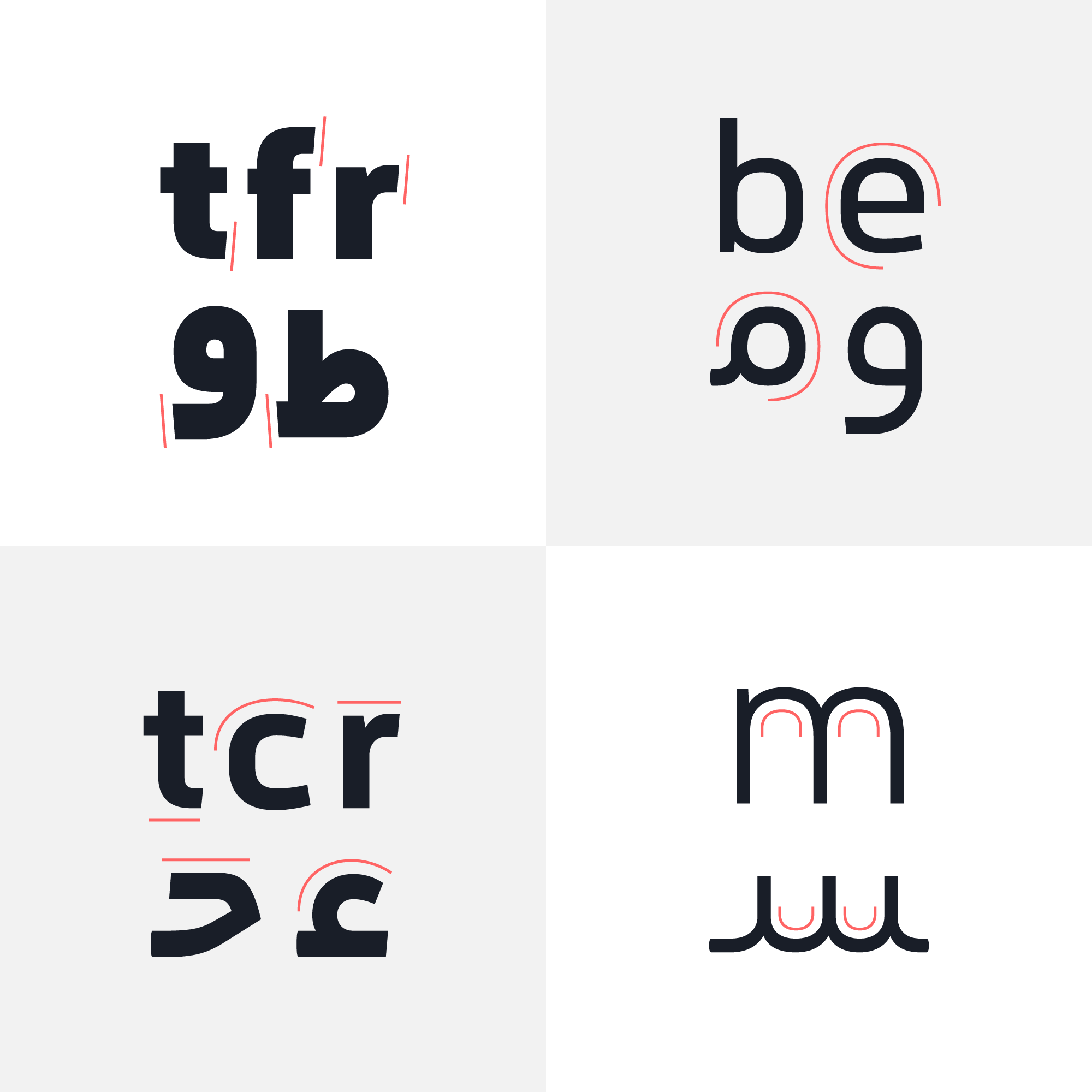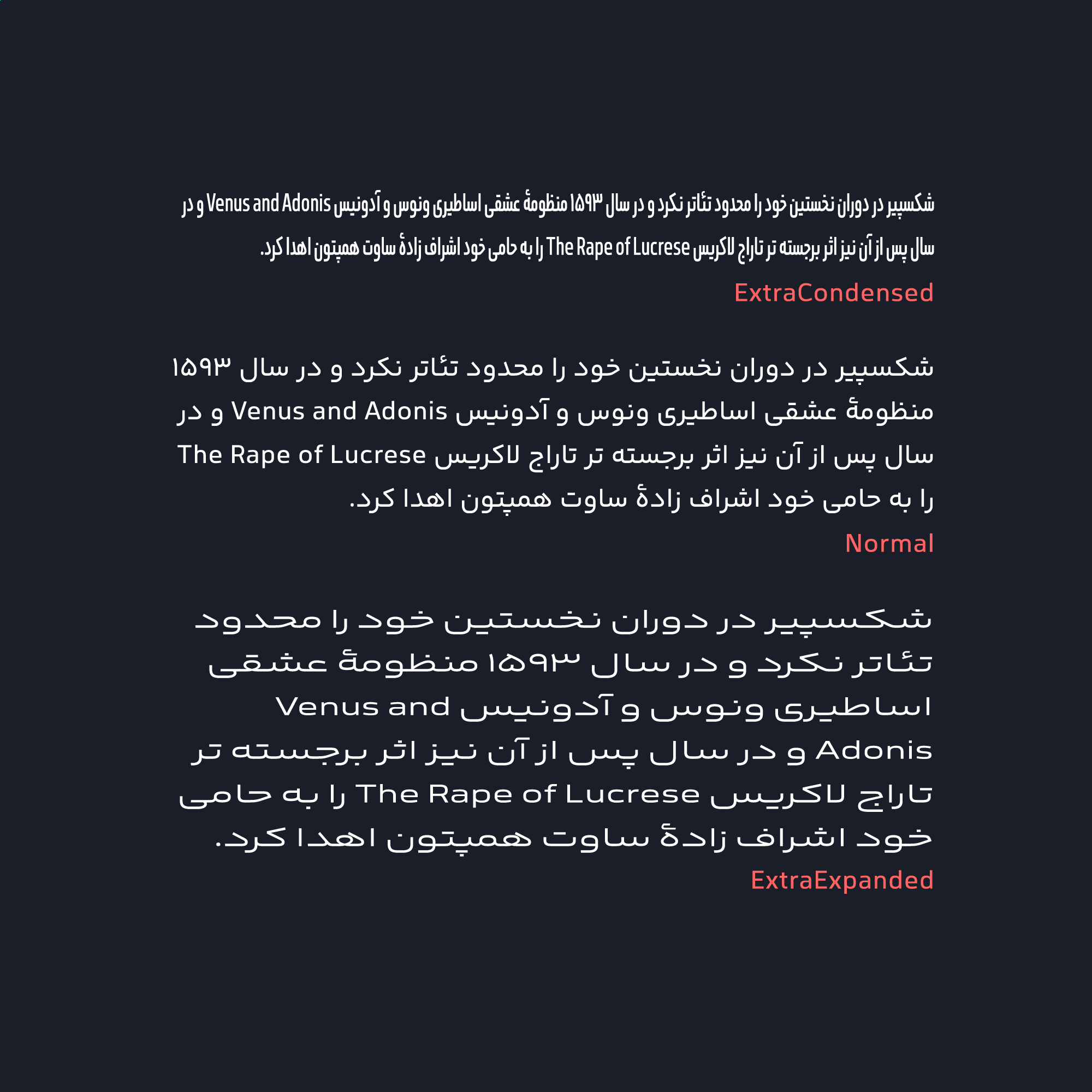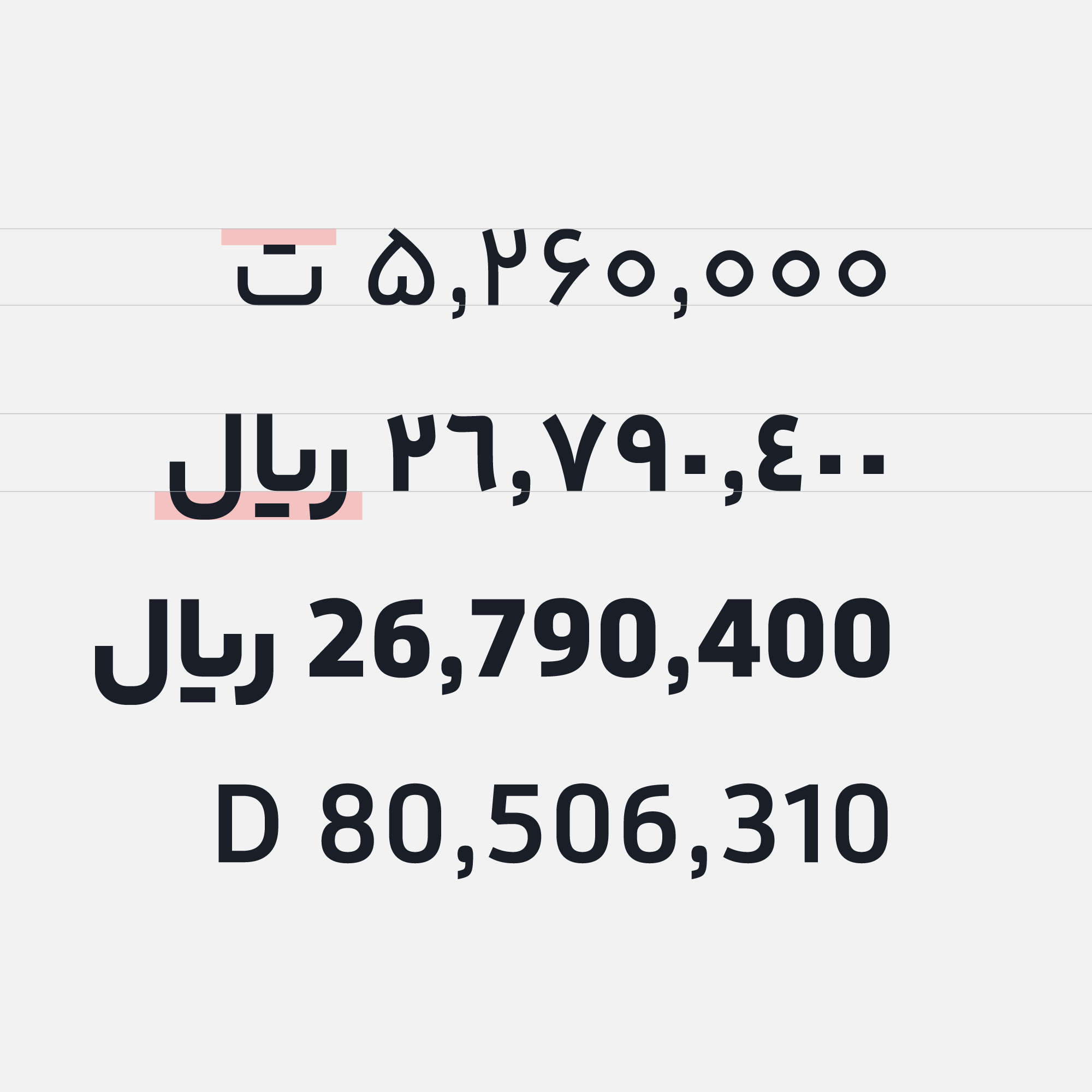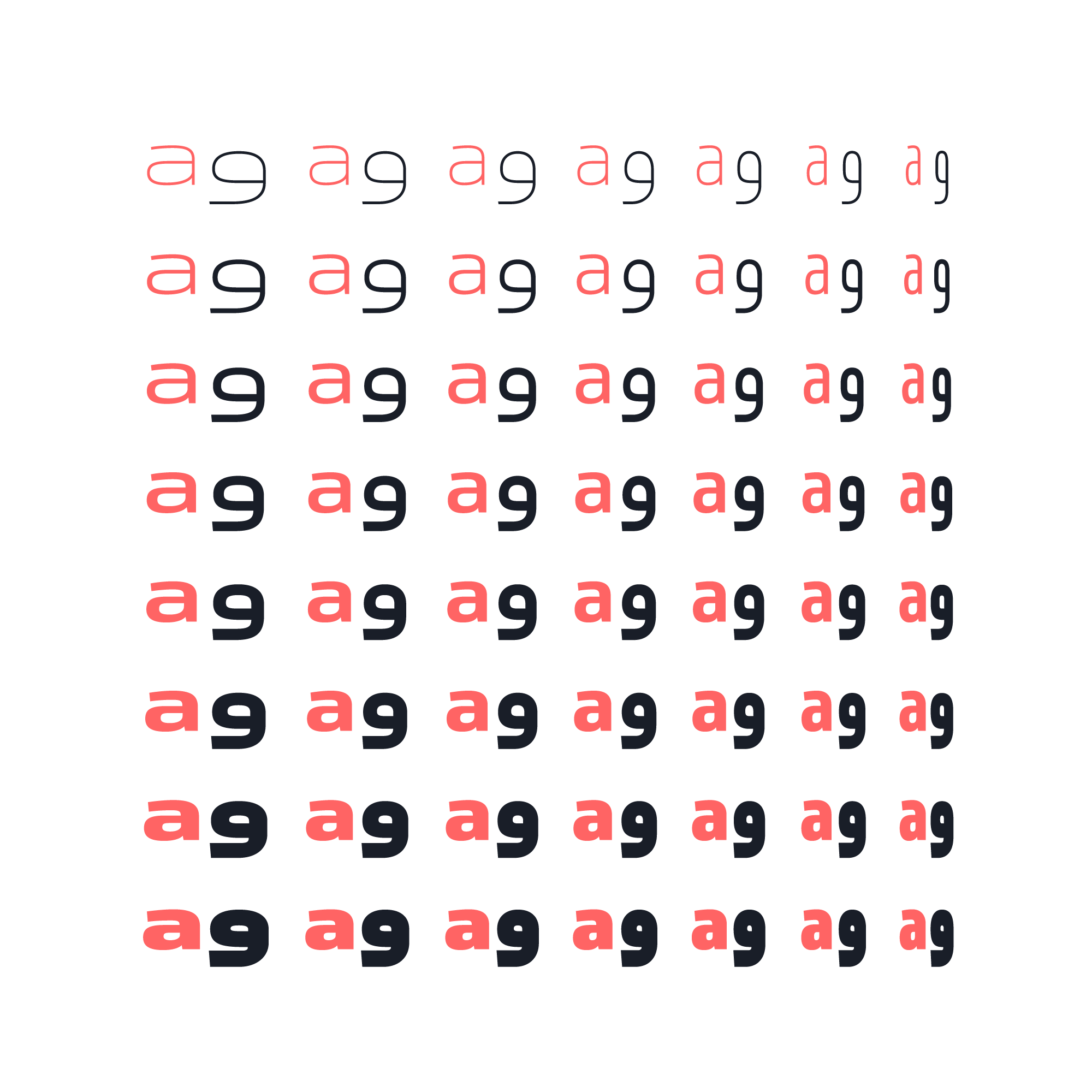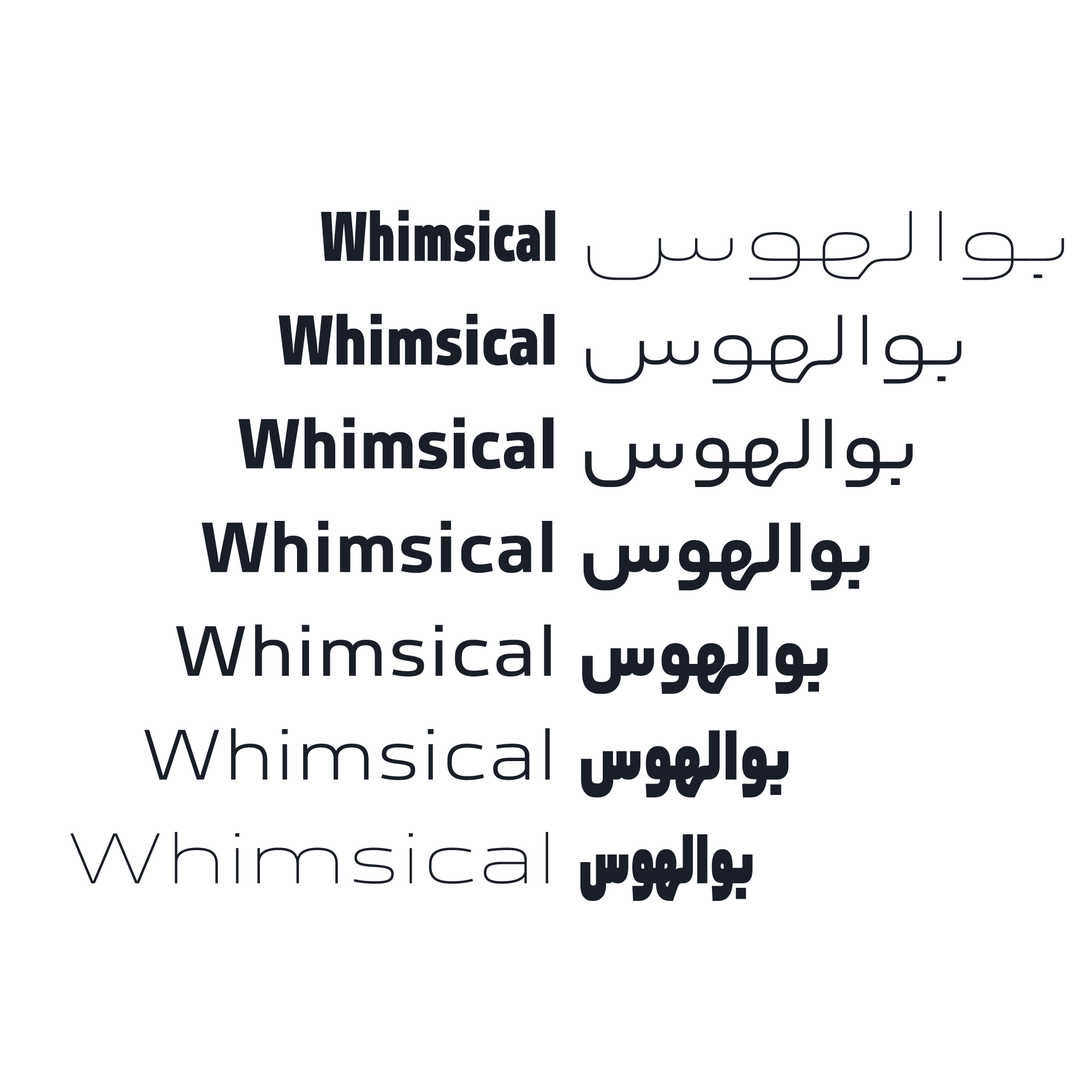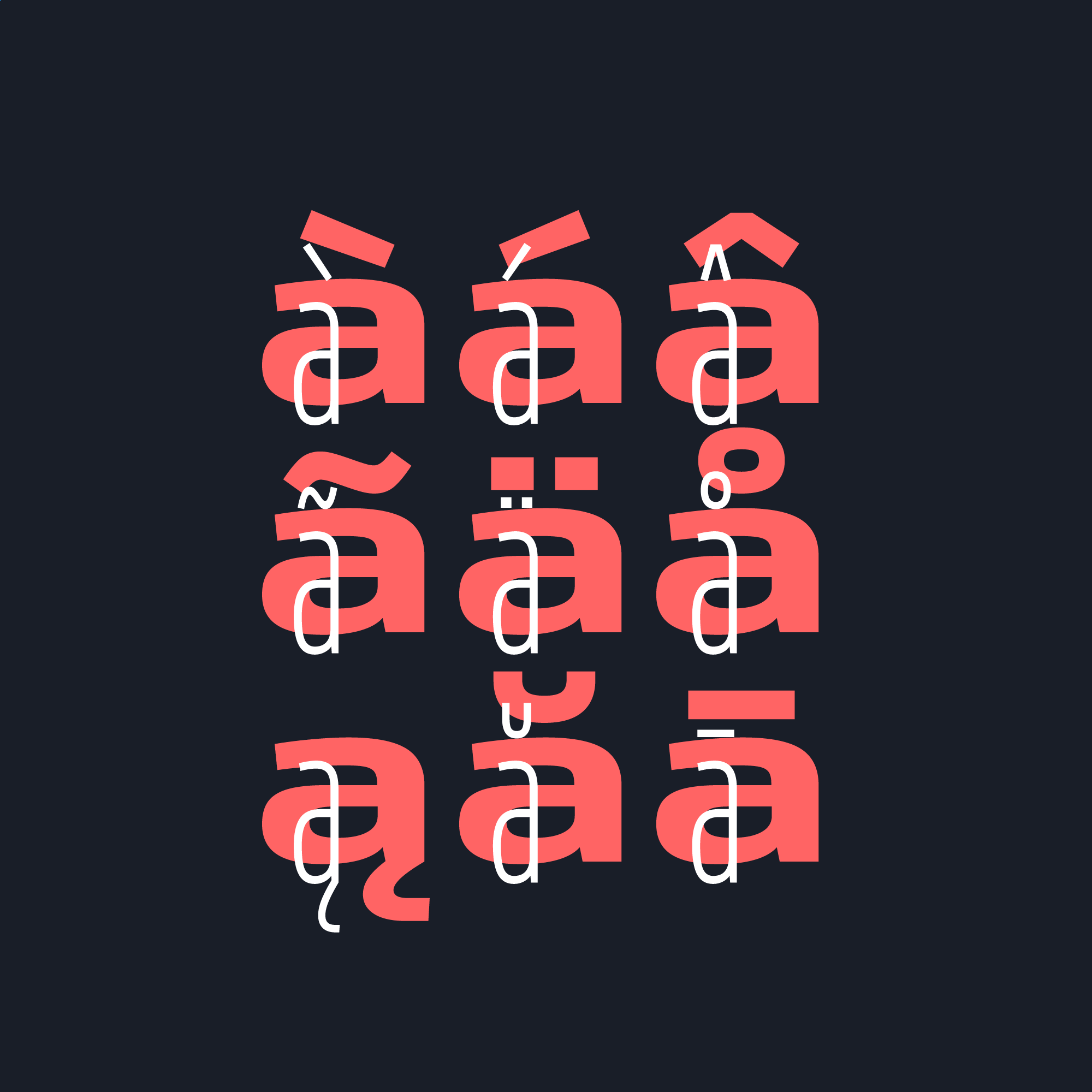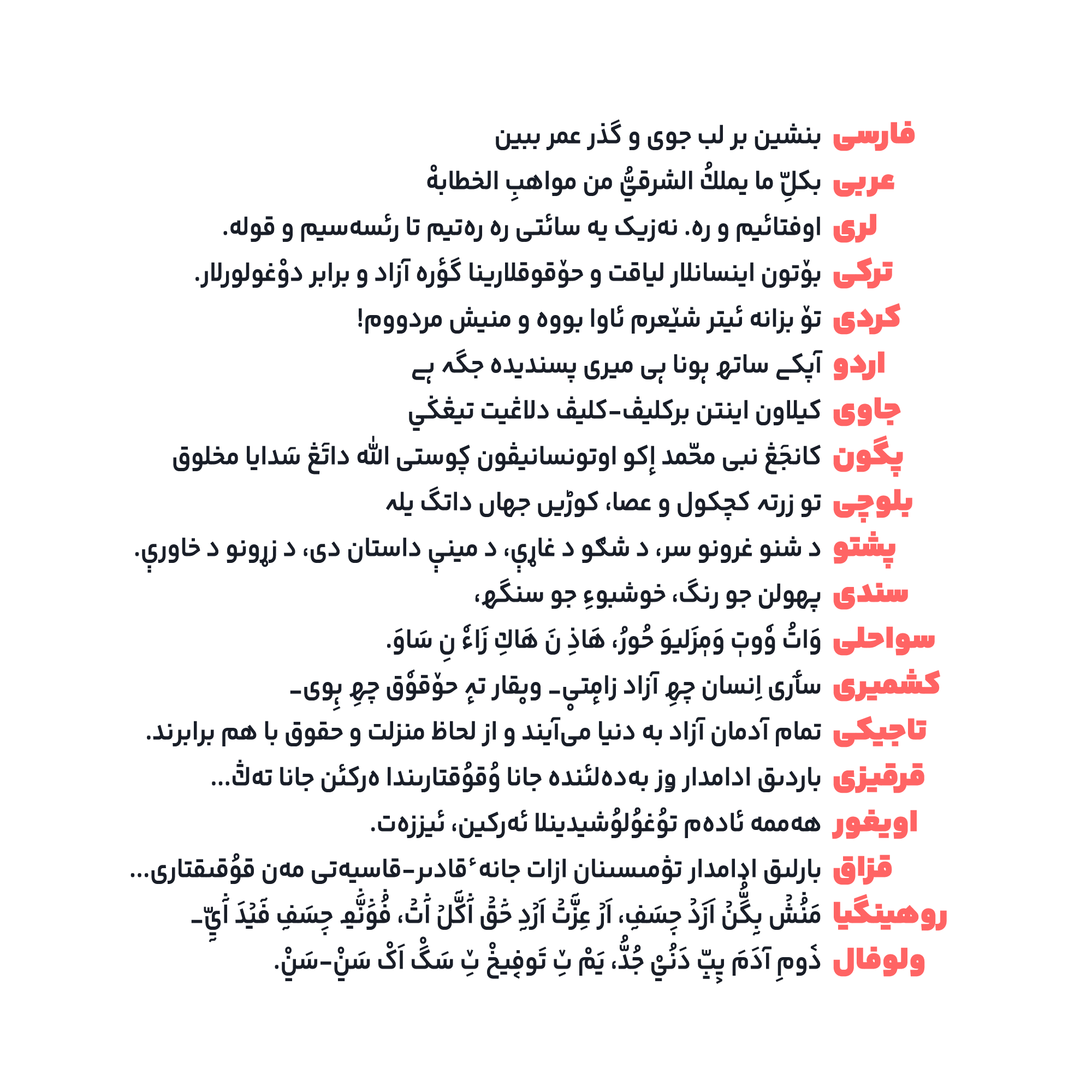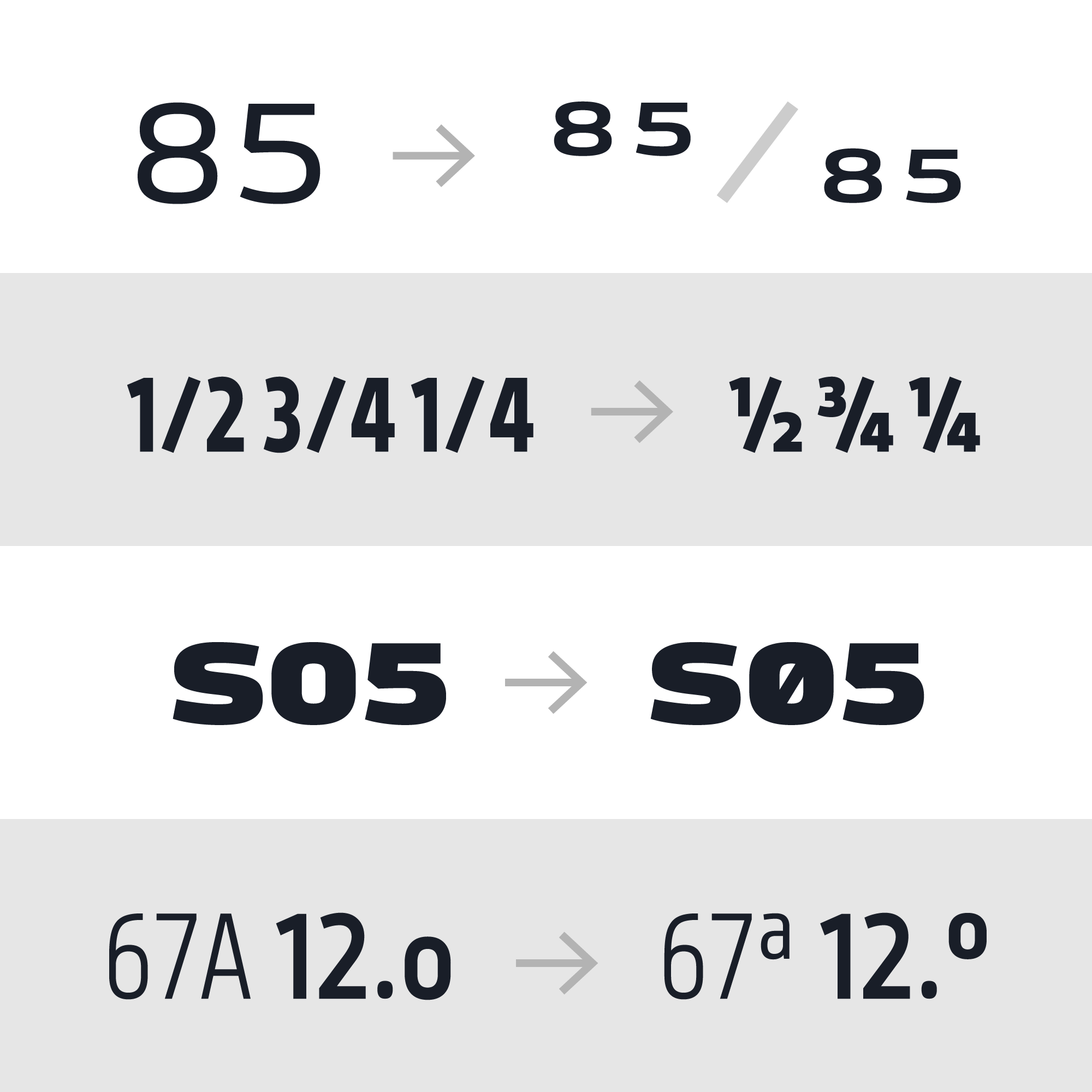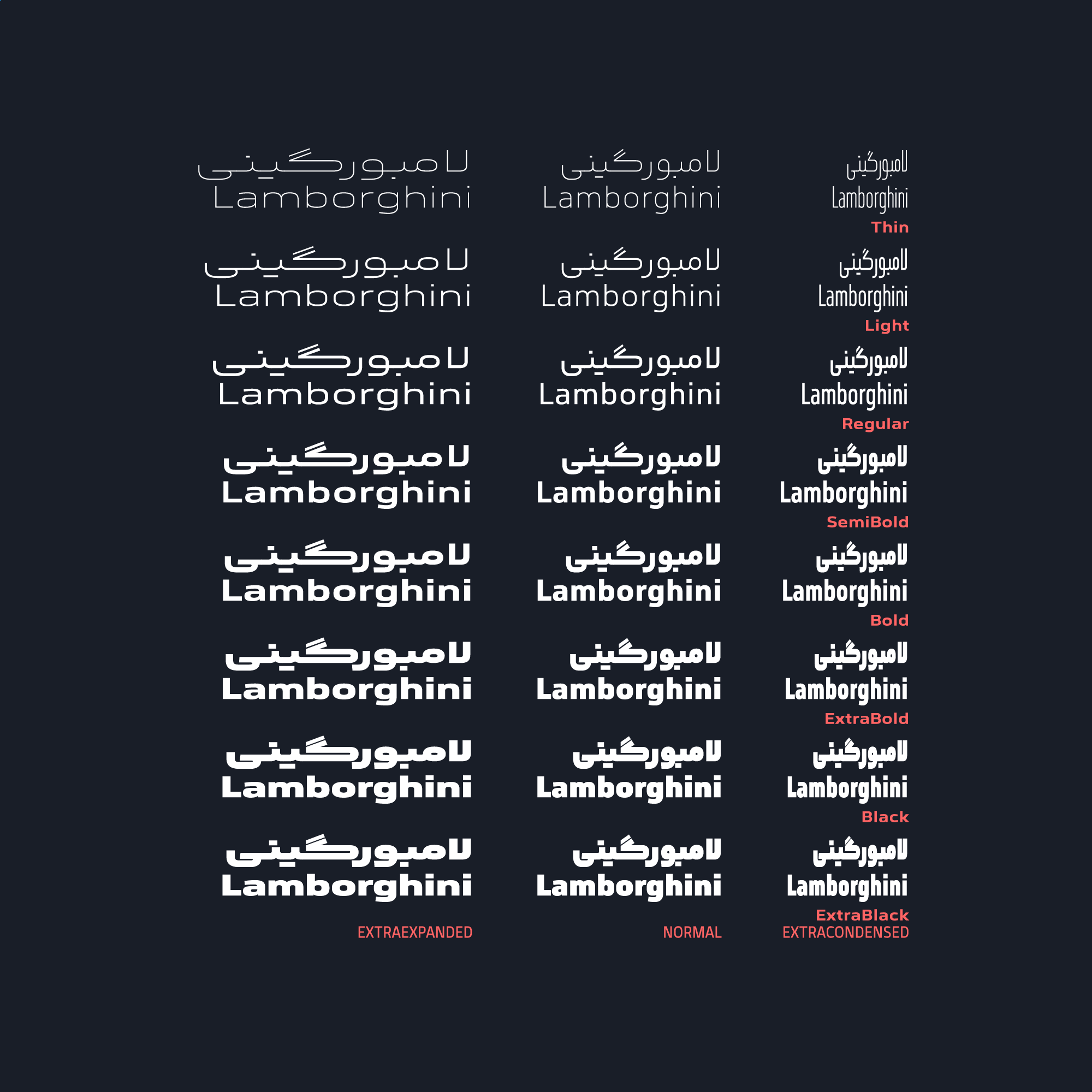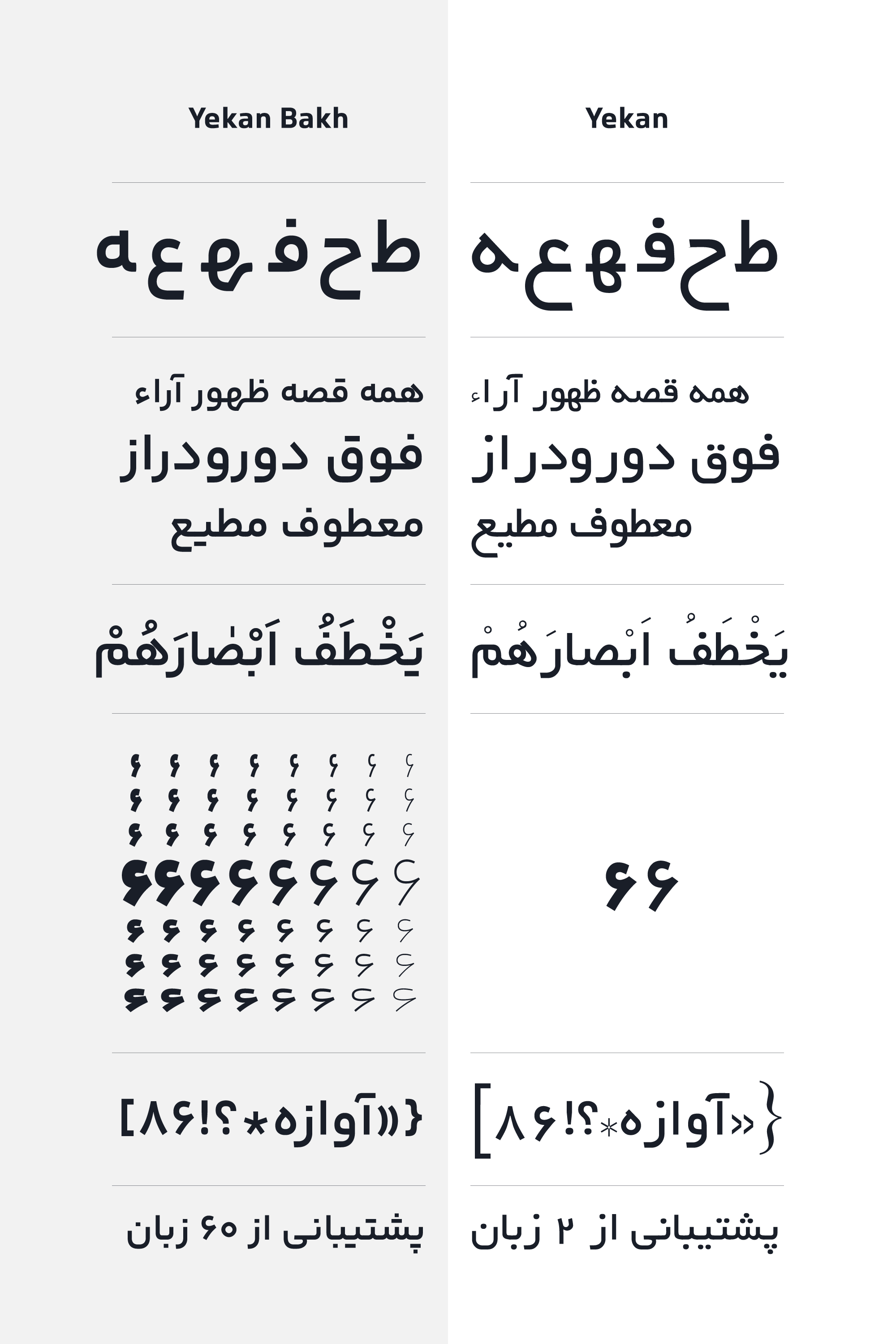
تنوع وزنها
فونت یکانبخ دارای ۸ وزن (Thin, Light, Regular, SemiBold, Bold, ExtraBold, Black, ExtraBlack) و ۷ سطح عرضی (ExtraCondensed, SemiCondensed, Normal, SemiExpanded, ExtraExpanded) و نسخهی وریبل است.
پوشش فوقالعادهی زبانهای جهان
فونت بیش از ۶۰ زبان را پوشش میدهد. (۲۰ زبان با خط عربی، ۱ زبان با خط ارمنی و ۴۱ زبان با خط لاتین) و در بیش از ۹۵ کشور قابل استفاده است.
نمونهی زبانهای مختلف با خط عربی
زبان بصری همآهنگ و الگوی دیزاین کاراکترهای فارسی، انگلیسی و ارمنی
اعداد همعرض
فاصلهگذاری در این اعداد مناسب زیرهمنویسی آنها بهصورت ستونی است.
یکان بخ ۱۷ واحد پولی را پوشش میدهد و در ۷۵ کشور قابل استفاده است.
با فعال کردن Stylistic Sets 6 میتوانید نمادهای اختصاصی ریال و تومان را فعال کنید و با فعال کردن Stylistic Sets 7 میتوانید تراز عمودی اعداد و نمادهای پولی را تنظیم کنید.
امکانات فونت برای اعداد لاتین
در فرآیند بازطراحی فونت یکان چه کارهایی انجام شد؟
- گسترش وزنهای فونت از ۲ به ۸ وزن و طراحی ۶ سطح عرضی؛ جمعا ۵۶ فونت
- طراحی اختصاصی و تکمیل کاراکترهای ۴۰ زبان با خط لاتین، ۲۰ زبان با خط عربی و خط ارمنی
- طراحی اختصاصی ۱۷ واحد پولی رایج
- طراحی و تکمیل علائم نگارشی و ریاضی مختلف و ضروری
- اعمال تغییر در جهت همآهنگسازی فرم، ضخامت و جثهی کاراکترها نسبت به هم
- بازبینی و تنظیم فاصلهگذاری بین حروف چسبیده و جدا و کرنینگ
- تغییر شکل کلی برخی از حروف مثل: د ه ه ه
- طراحی کاف کشیده و ی معکوس
- طراحی جدید فرم نقطهها
- بازبینی فرم، ضخامت و جثهی اعرابها و تنظیم موقعیت آنها
- کوچک شدن کاسهی «ع» و «ح» و کوتاه شدن کرسی پایین بهمنظور سازگاری با فضای رابط کاربری
فونت یکانبخ در کاربرد